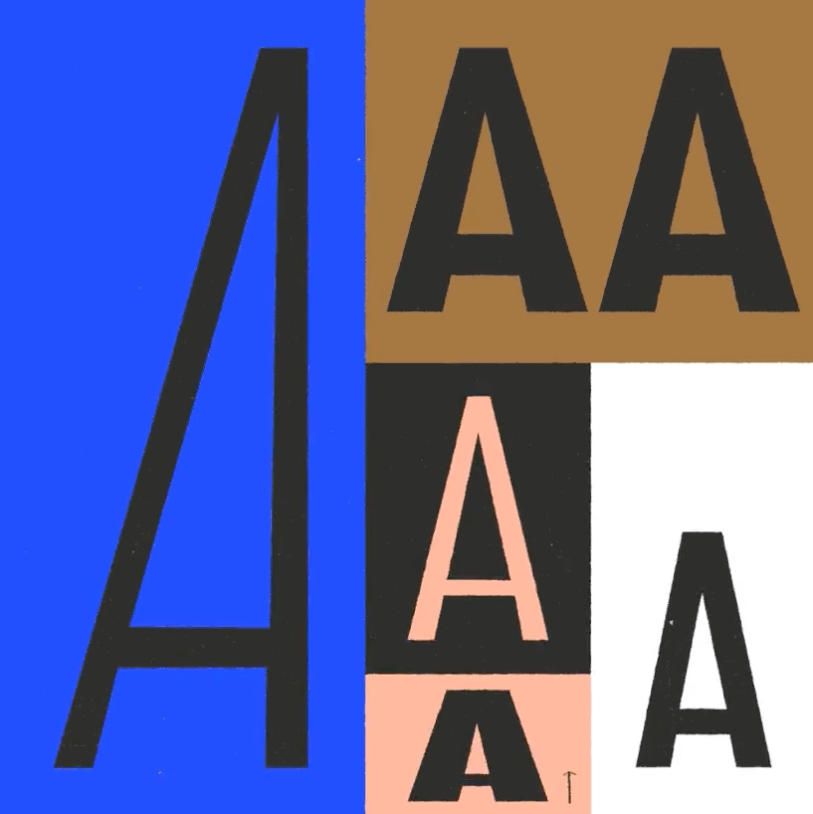
Unidos por la tipografía: Descubre 5 proyectos inspiradores de la comunidad en el 36 Day of Type
El 36 Day of Type es un evento anual que cautiva a la comunidad creativa y a los apasionados de la tipografía. A lo largo de 36 días intensos, personas de todo el mundo comparten proyectos únicos que desafían los límites de las letras y los números.
Es un encuentro lleno de inspiración, aprendizaje y colaboración, donde la magia de la tipografía tiene más presencia que nunca en redes sociales y se fomenta la conexión entre entusiastas y expertos de esta fascinante disciplina.
Este año se ha celebrado su décima edición entre el 10 de abril y el 15 de mayo, por este motivo te compartimos 5 proyectos destacados de la comunidad en distintas convocatorias. Descubre la diversidad y creatividad que han definido este evento anual. ¡Sumérgete en el mundo de la tipografía y déjate inspirar!
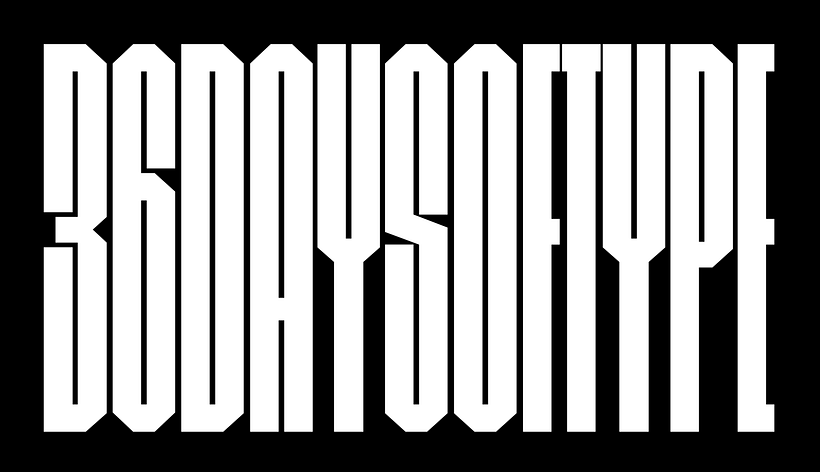
36 days of type 10th por DSORDER (@dsorder)
Empezamos por la colección de números creada por Martí Serra, en ella presenta un enfoque único basado en un ambigrama, permitiendo que los números se lean de manera girada y jugando con las formas y simetría.
Los acabados metálicos cromados agregan un toque de elegancia adicional. El proceso creativo comienza con bocetos en papel y luego se traslada al entorno digital utilizando Illustrator para crear formas simples y limpias. Finalmente, se completa el proceso en 3D, donde se logran volúmenes, iluminación y acabados metálicos, junto con la compleja interconexión de las formas.
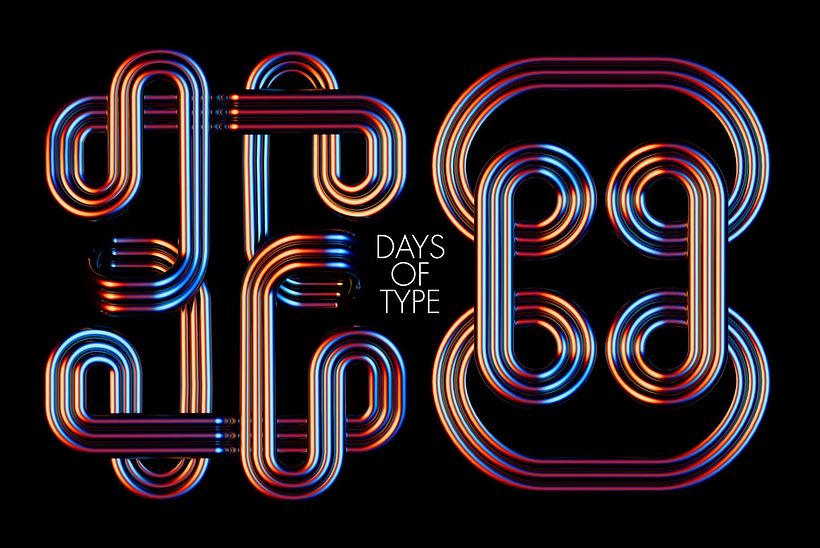
36 Days of Type por Mat Voyce (@matvoyce)
En su quinto año de participación en el 36 Day of Type, Mat decidió hacer algo especial. Animó sus tipografías favoritas, nombradas en honor a cada letra del día, en lugar de utilizar un estilo ilustrativo. Fue invitado como colaborador especial para el 'Día 22 - V' y utilizó la fuente 'Vektra'. Además, contó con Dom de Tone Test Studio, quien creó una banda sonora personalizada para su proyecto.
36 characters of type por Zinkete (@zinkete)
Te presentamos un divertido proyecto del 36 Day of Type que te transporta a un mundo tridimensional. En esta proyecto de Zinkete, cada letra cobra vida a través de personajes en 3D, cada uno con su propio concepto simbolizando. Seguro que te va sorprender.
Descubre cómo estas letras en 3D dan vida a la imaginación y te invitan a explorar la diversidad de formas y conceptos en el mundo de la tipografía.
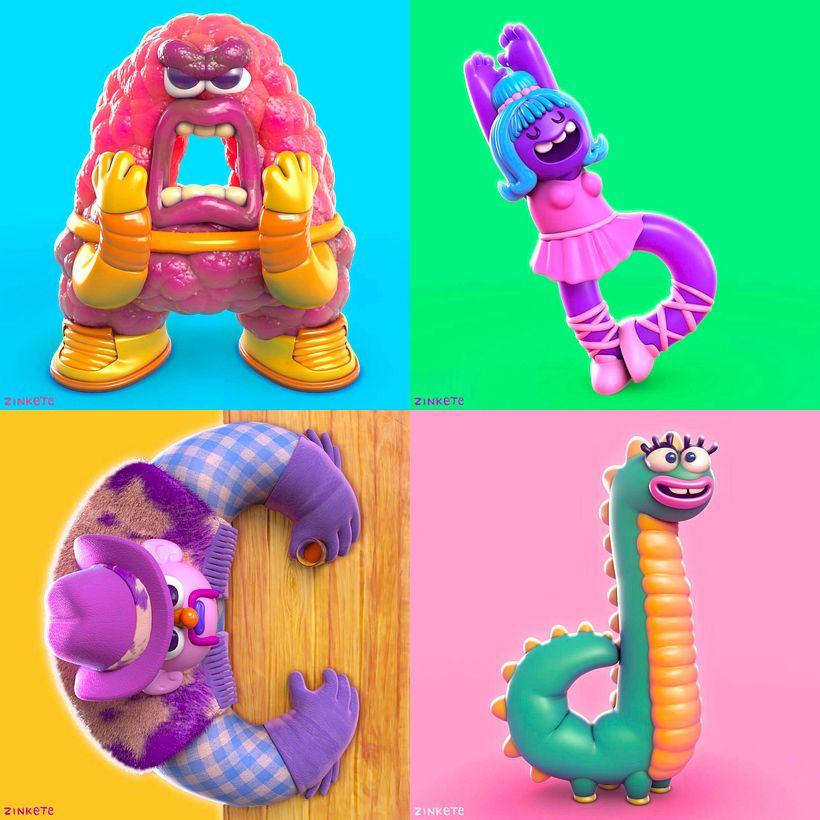
36 Tools for 36 Days of Type por João Varela (@joaoistyping)
Joäo en su participación en el 36 Days of Type con este proyecto, rompió con las reglas y estilos tradicionales de la caligrafía contemporánea.
Ha utilizado herramientas poco convencionales, como palillos de dientes, esponjas de baño, dedos e incluso una pistola de agua, on ellas ha creado un alfabeto único. Cada letra es el resultado de una experiencia distinta y sorprendente, demostrando cómo con nuevas herramientas se puede dar forma a nuevos estilos de escritura.
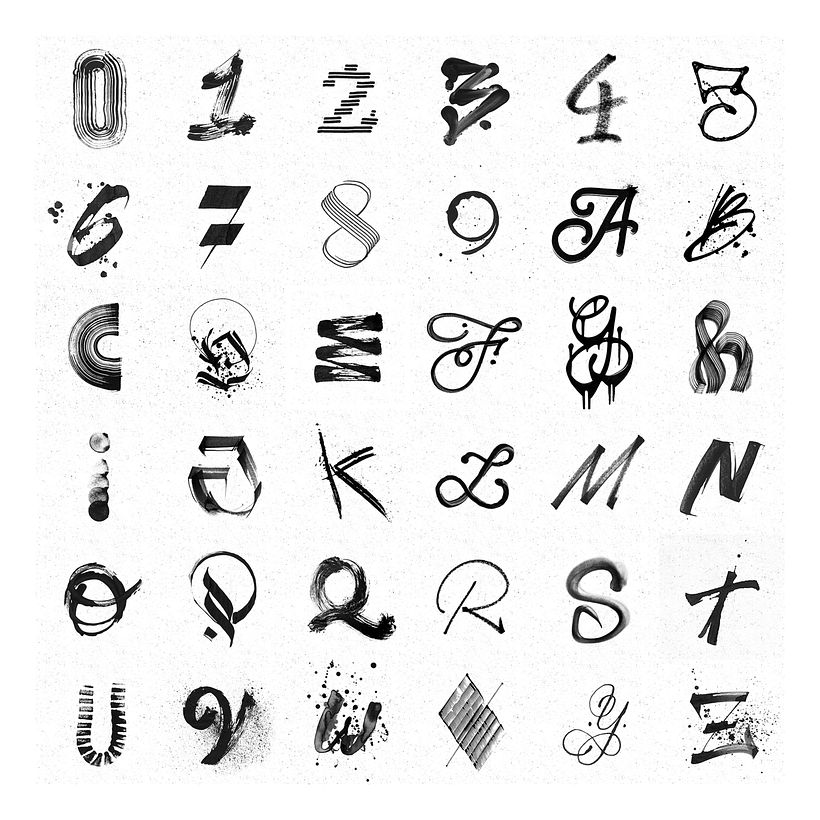
36 days of type por Eduardo Morgan (@eduardo_morgan)
Eduardo Morgan ha realizado un proyecto fascinante utilizando Adobe Fresco, en el cual las formas de las letras parecen surgir como trazos de pintura con un efecto de volumen sorprendente. Cada letra adquiere vida propia con una apariencia artística que evoca pinceladas y texturas que vuelan en el espacio.